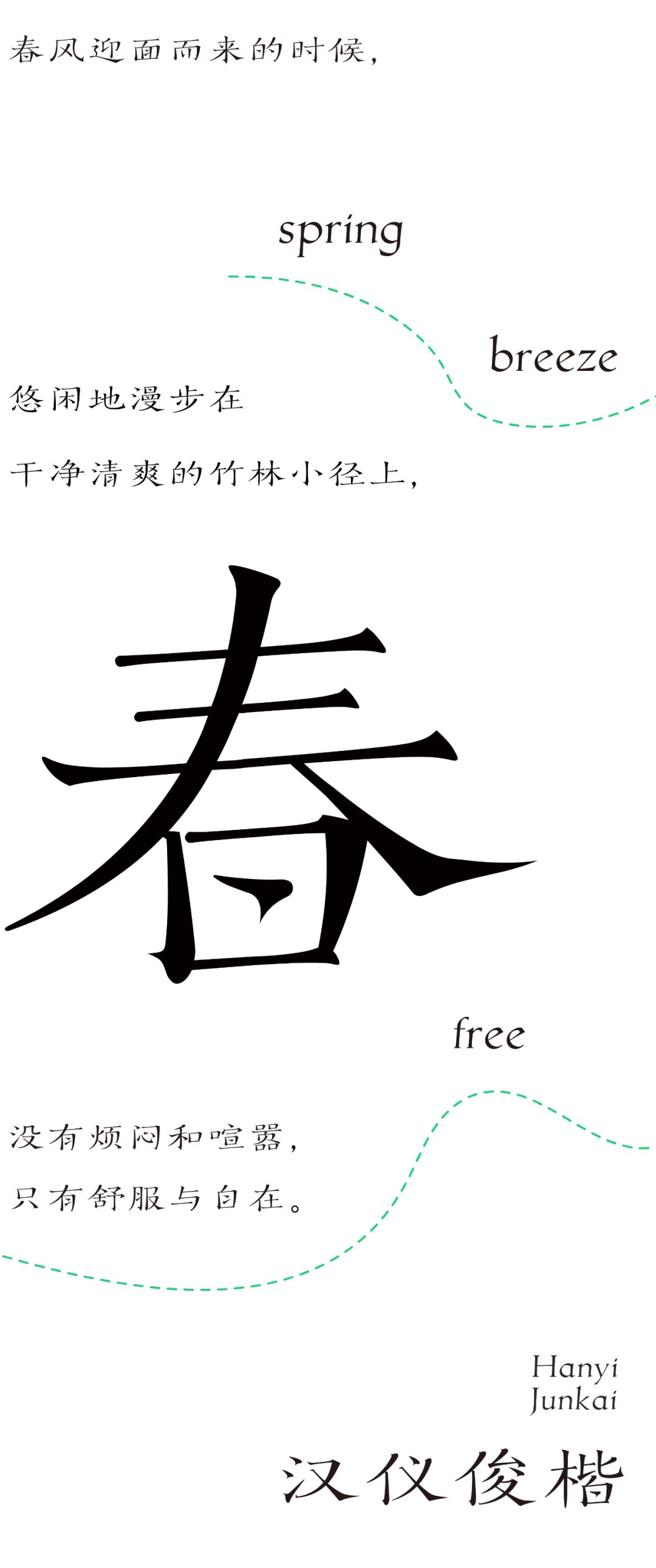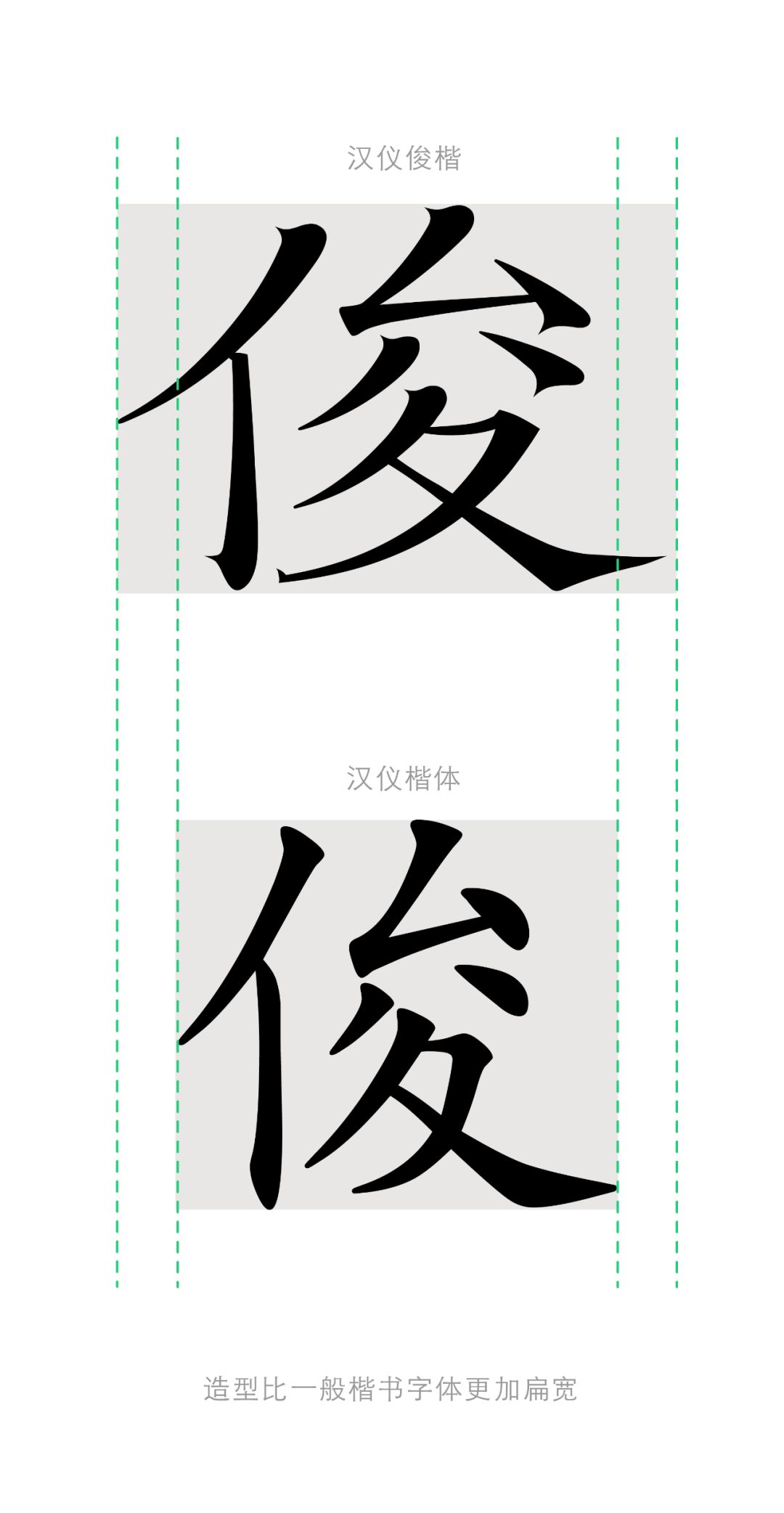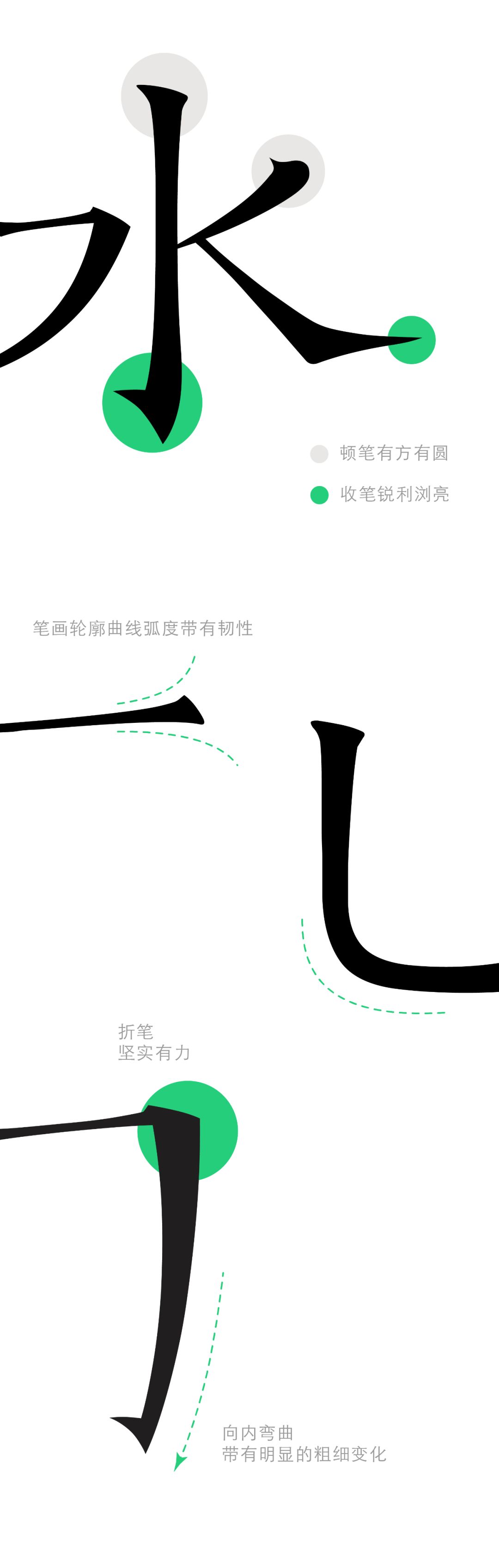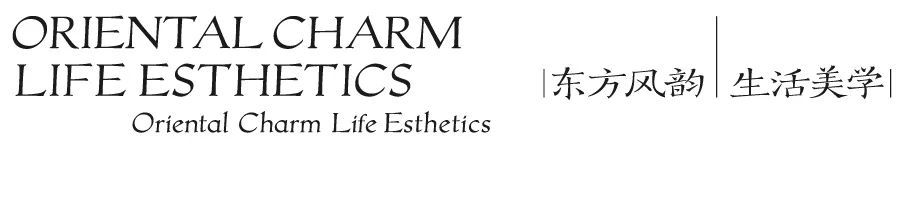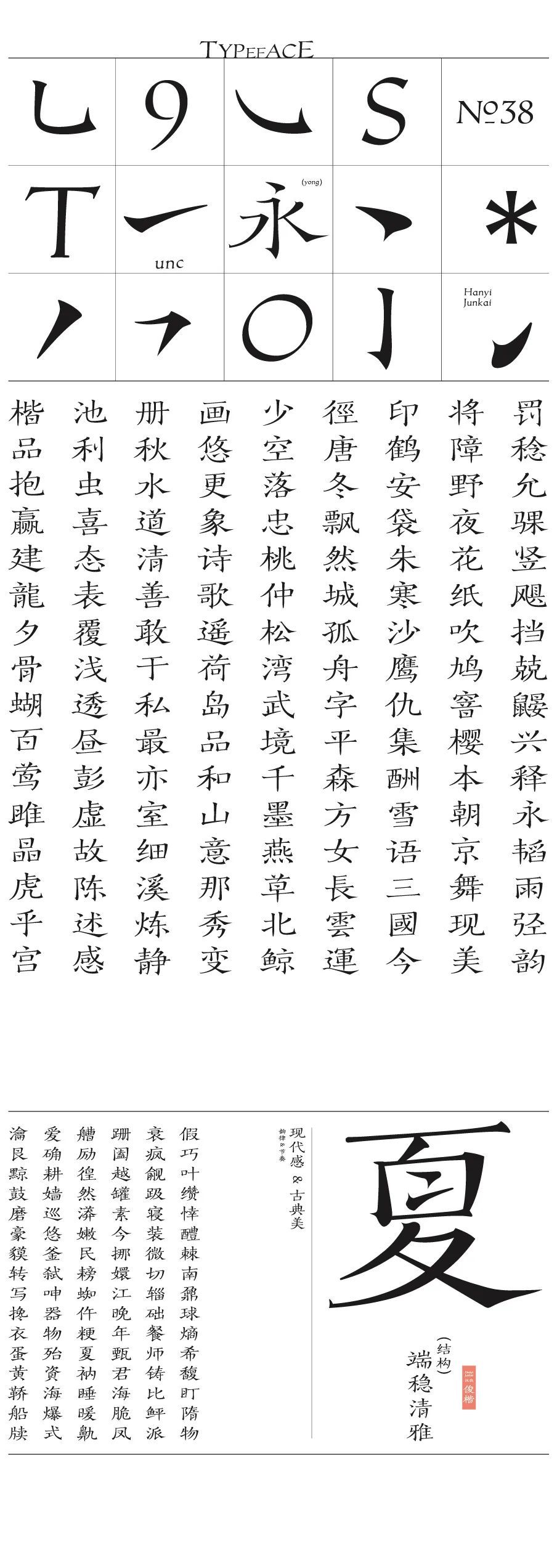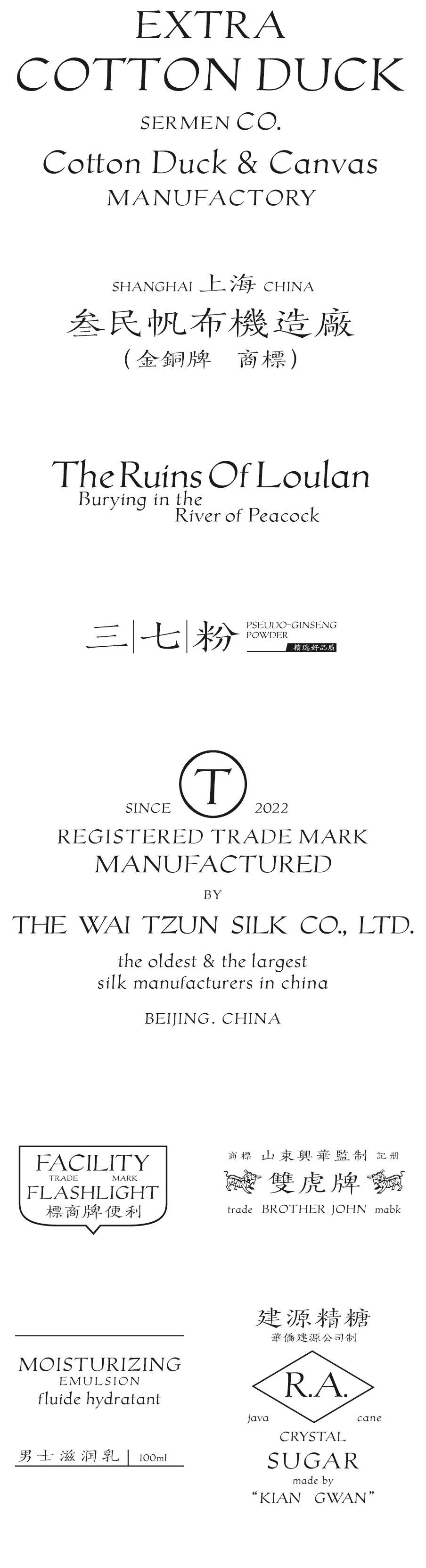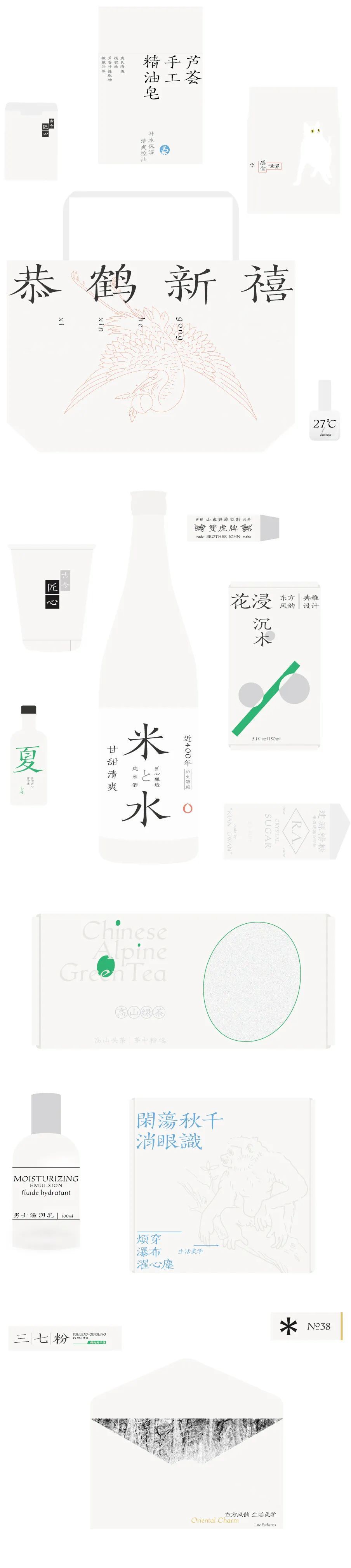
汉仪俊楷是一款清新闲适的创意楷书字体,由汉仪字库签约设计师谷龙创作。该字体通过富有张力的线条、俊朗的笔触,为读者营造出一片远离凡尘、长林丰草之地,仿佛置身于这茂林修竹中吟风弄月、谈古论今。
字形特征
汉仪俊楷造型扁宽,重心稍高,笔画外张,带来文质彬彬的感觉。
笔画特点
汉仪俊楷笔画造型俊朗,单个笔画有明显粗细对比,纤细处尖锐清晰明亮、停顿处坚实有力;起笔收笔有粗有细、有方有圆,相互照应;曲线轮廓富有张力,传递出一股韧劲。
西文设计
西文字体造型以上个世纪20年代装饰艺术时期流行的西文衬线体风格为参考,并将部分汉字笔画部件融入其中。